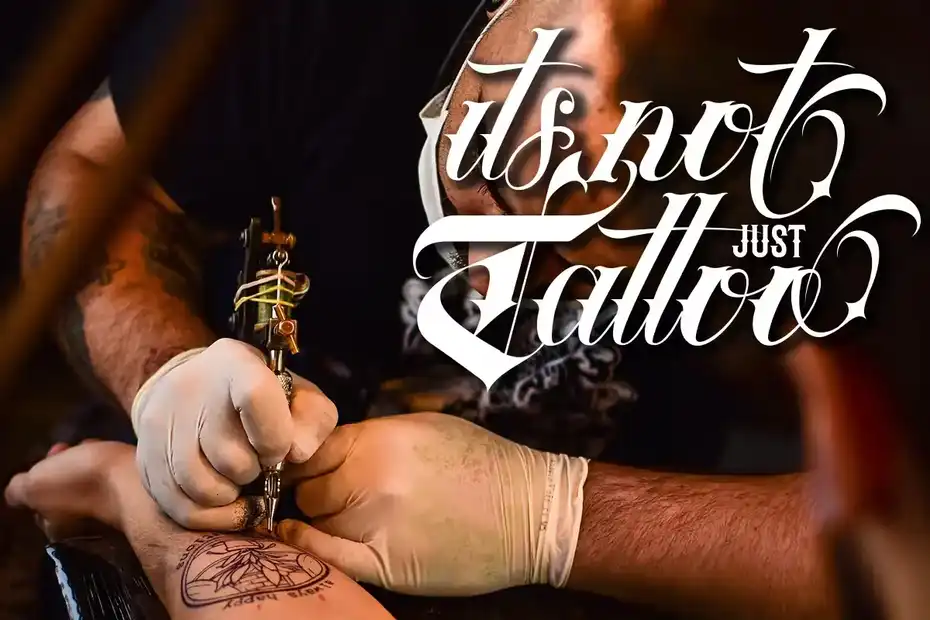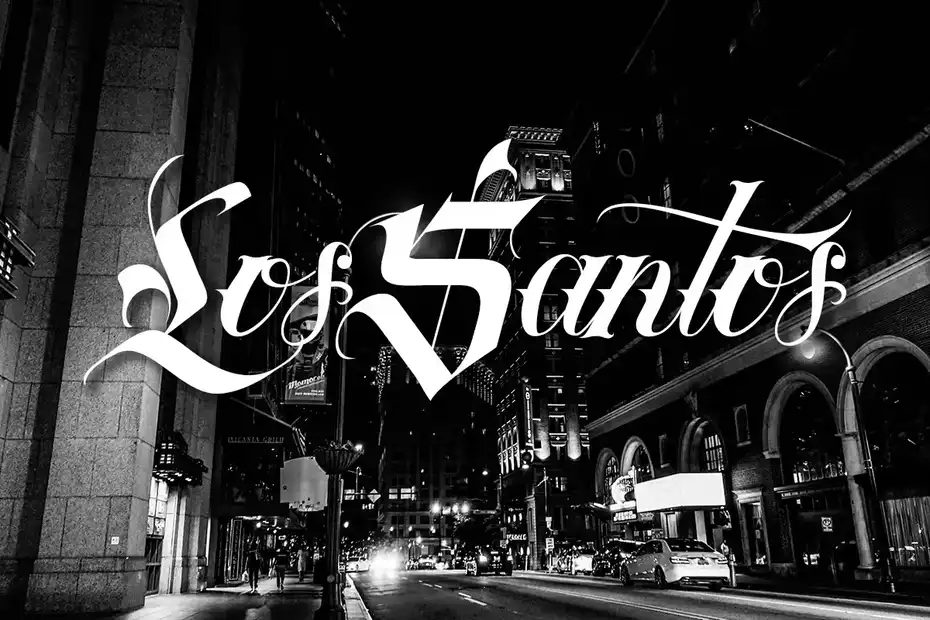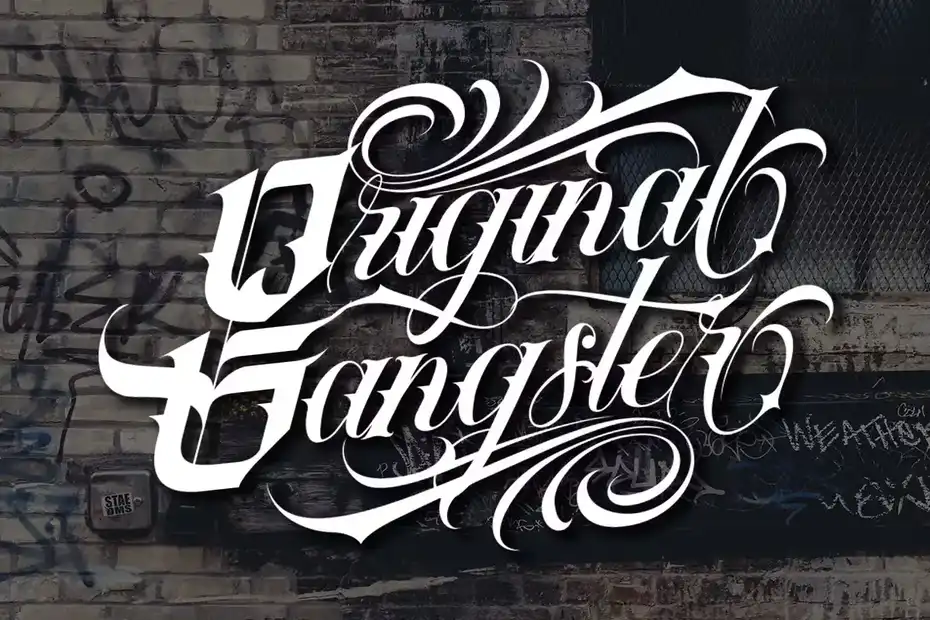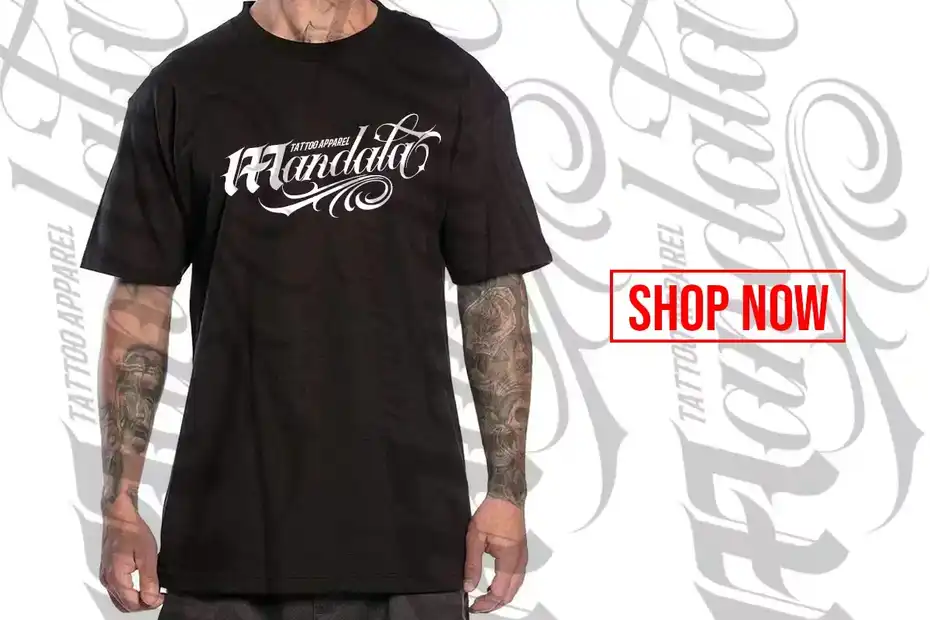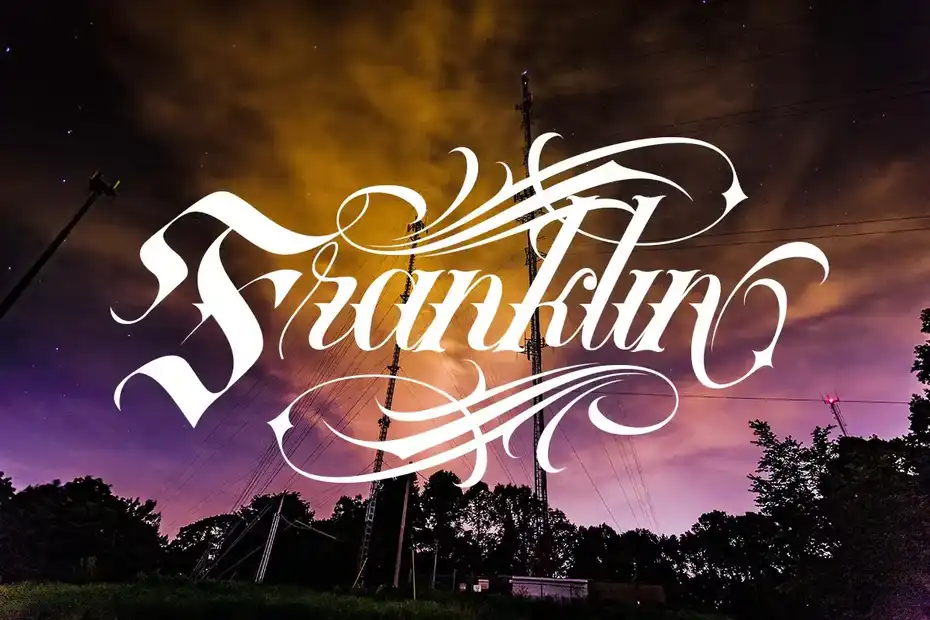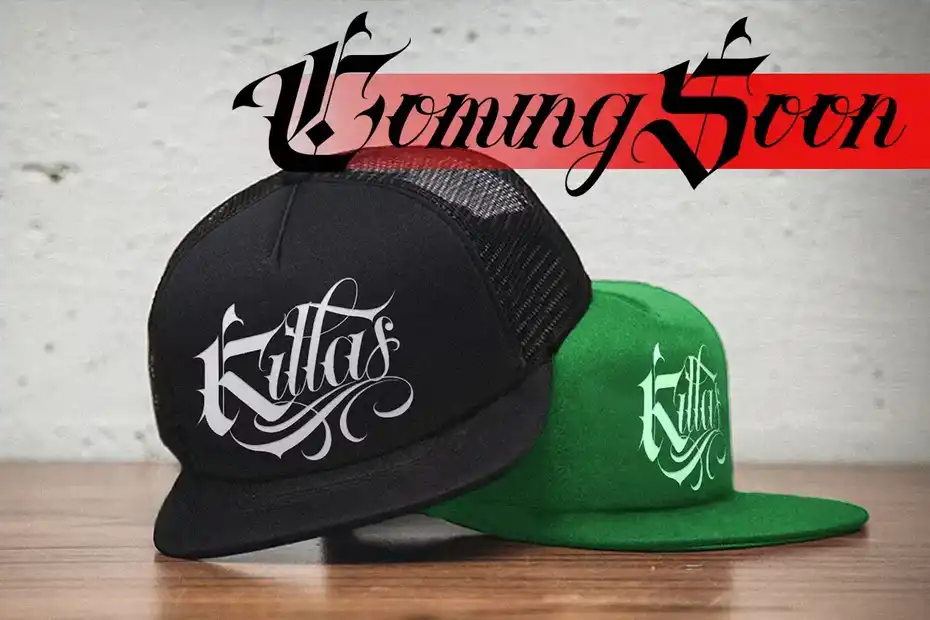
معرفی سبک و کاربردهای هنری دانلود فونت انگلیسی Tribal
دانلود فونت تاتو Tribal Font یک انتخاب جسورانه و متمایز برای طراحان و تاتو آرتیست های است که به دنبال خلق آثاری با حال و هوای قومی، بومی و مرموز هستند. این فونت دکوراتیو (Decorative) با الهام از نقش و نگار های باستانی و خطوط تهاجمی قبیله ای طراحی شده و پتانسیل بالایی برای استفاده در پروژه های خاص مانند طراحی تاتو، کاور آلبوم های موسیقی، پوستر های هنری و لوگو تایپ های خلاقانه دارد. اگر پروژه شما نیاز به تایپوگرافی ای دارد که حس قدرت، قدمت و فرهنگ های بدوی را منتقل کند، این فونت با ساختار هندسی و شارپ خود، روحی تازه و متفاوت به طرح های گرافیکی شما می بخشد و مخاطب را در نگاه اول مجذوب میکند.